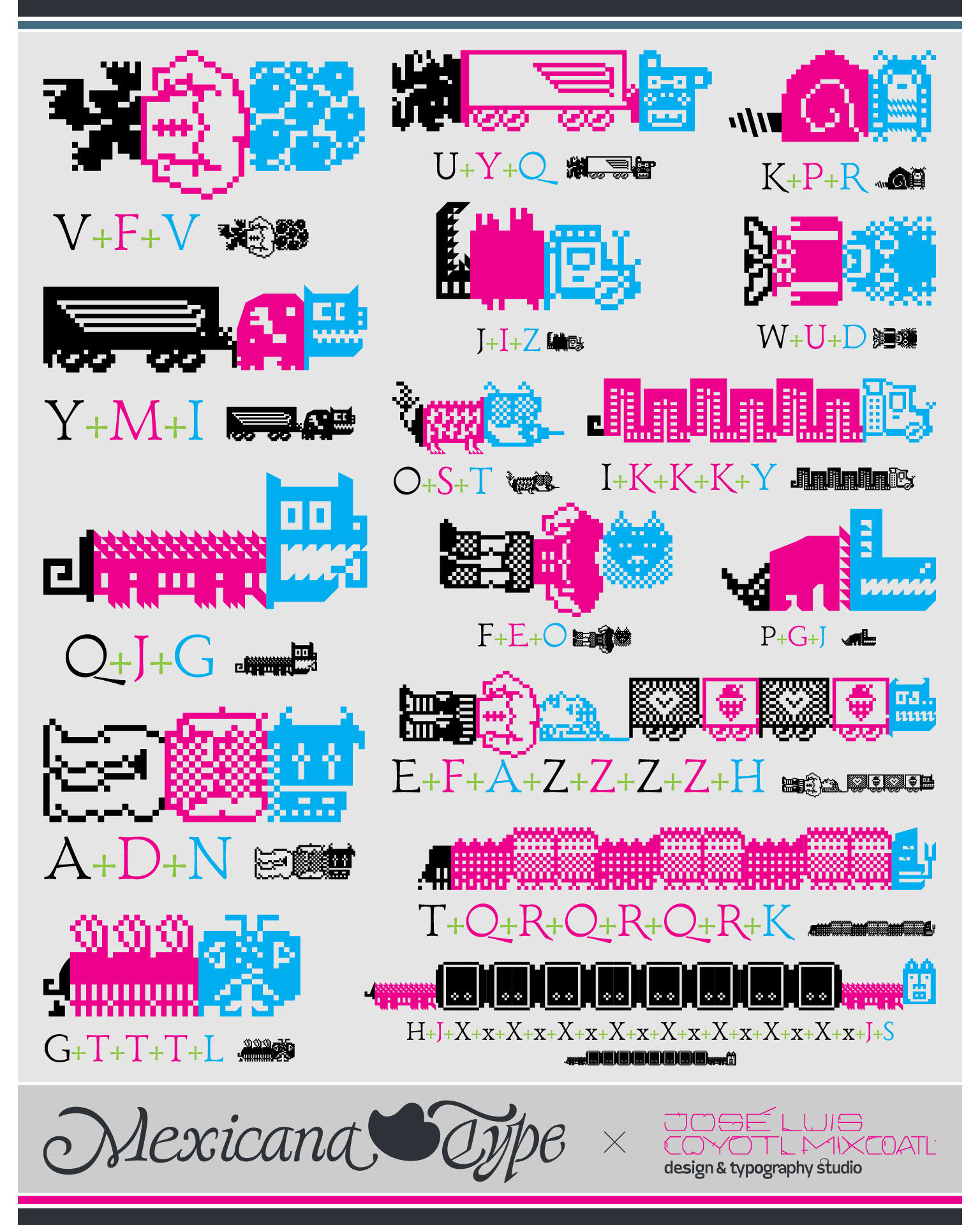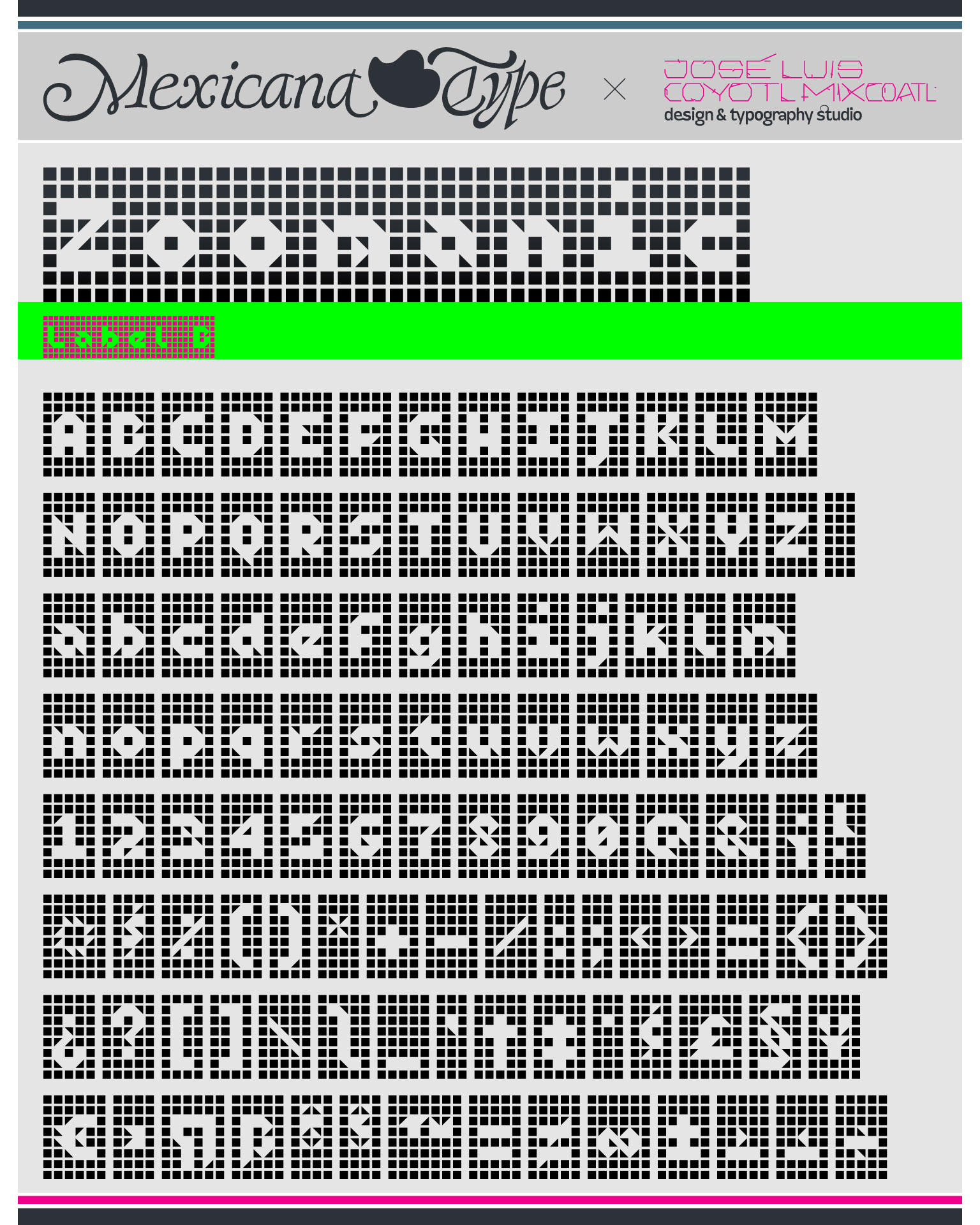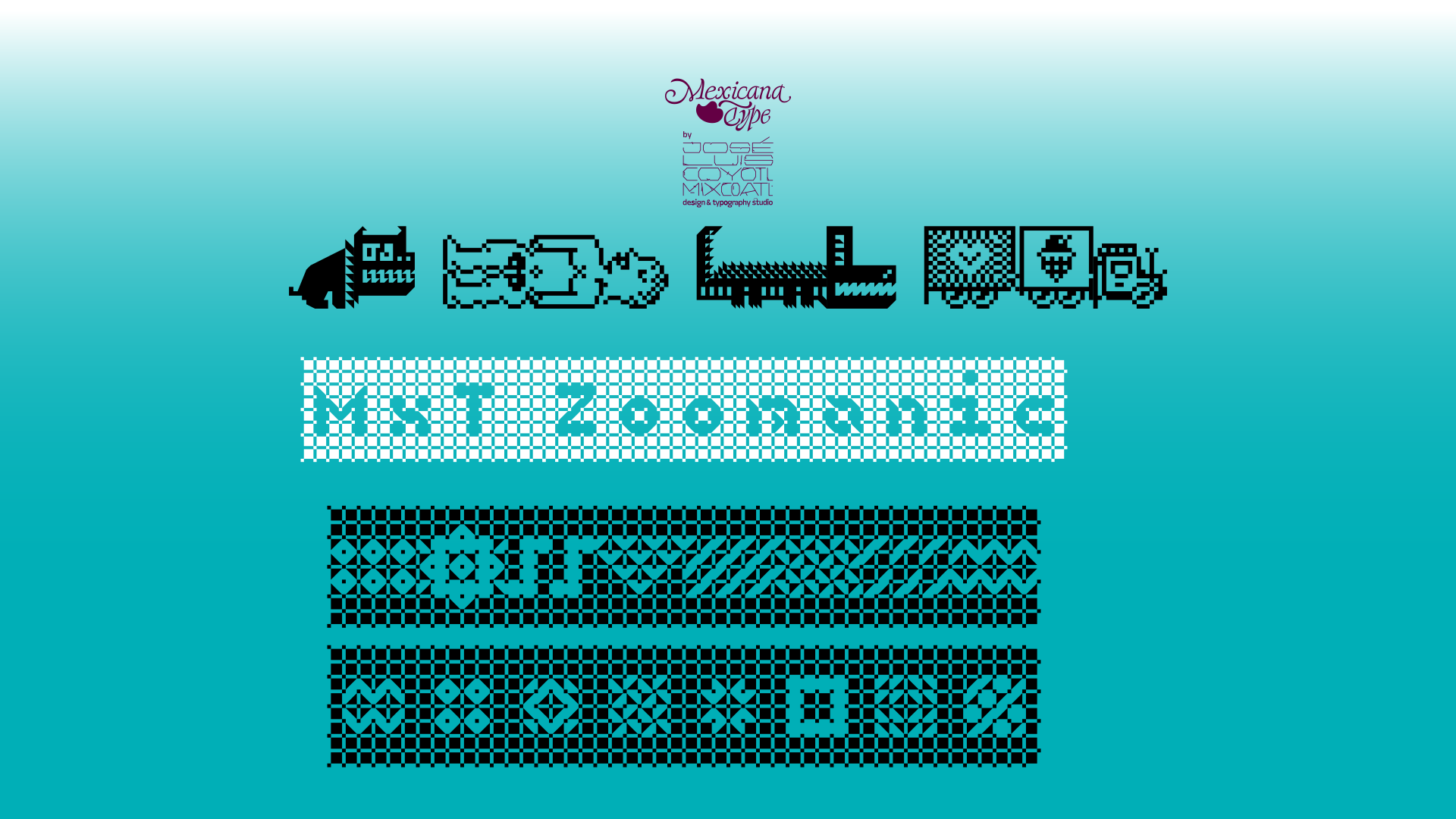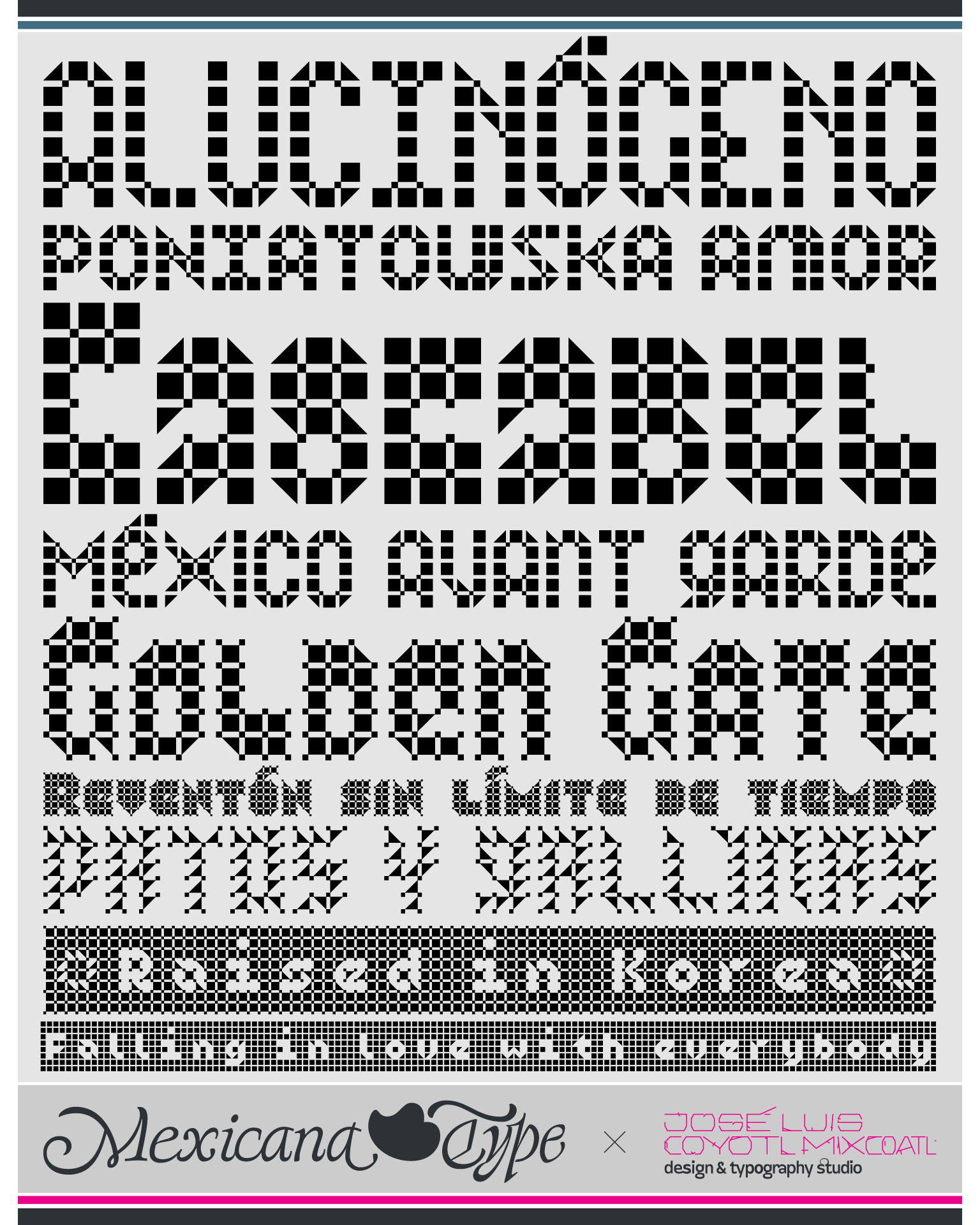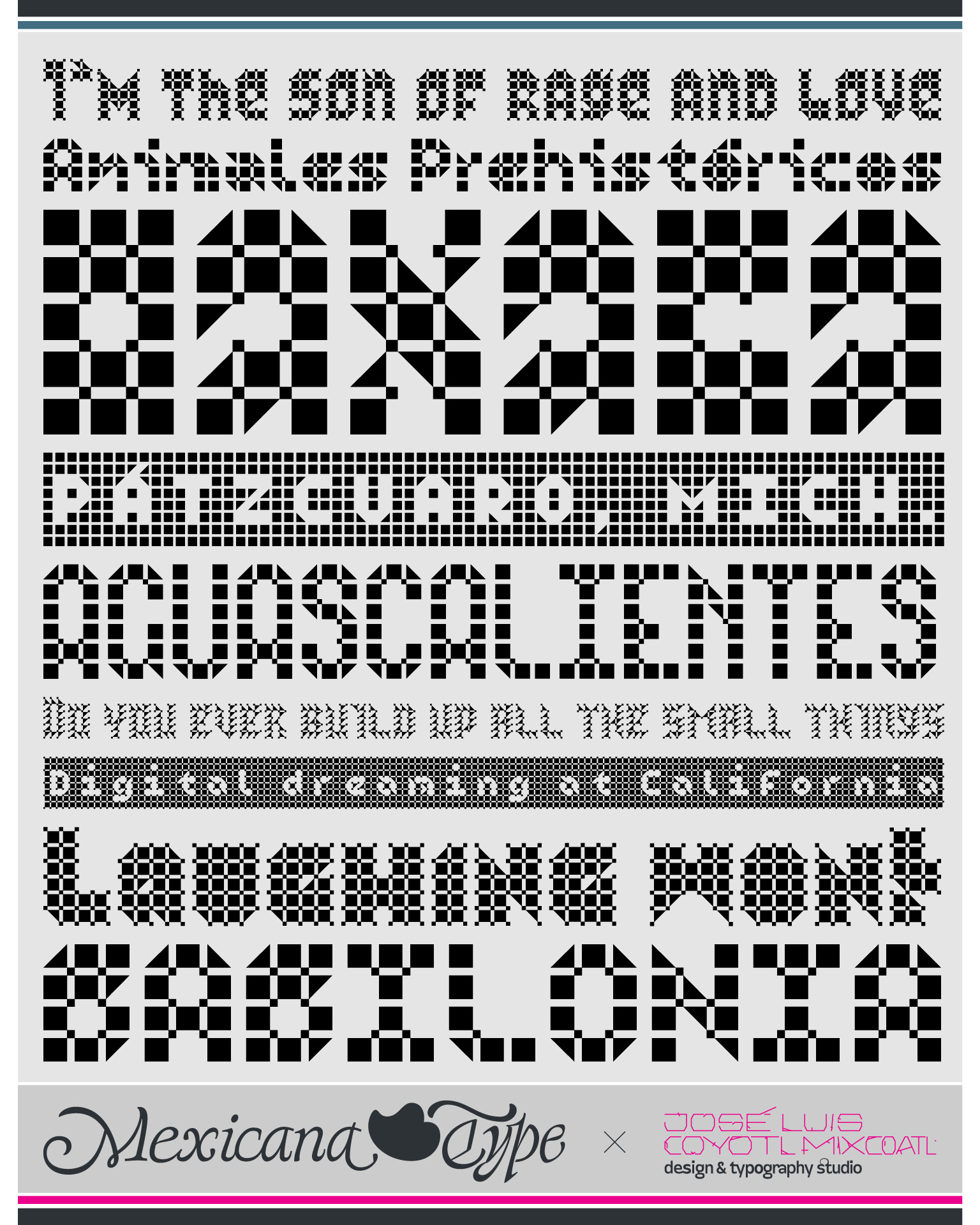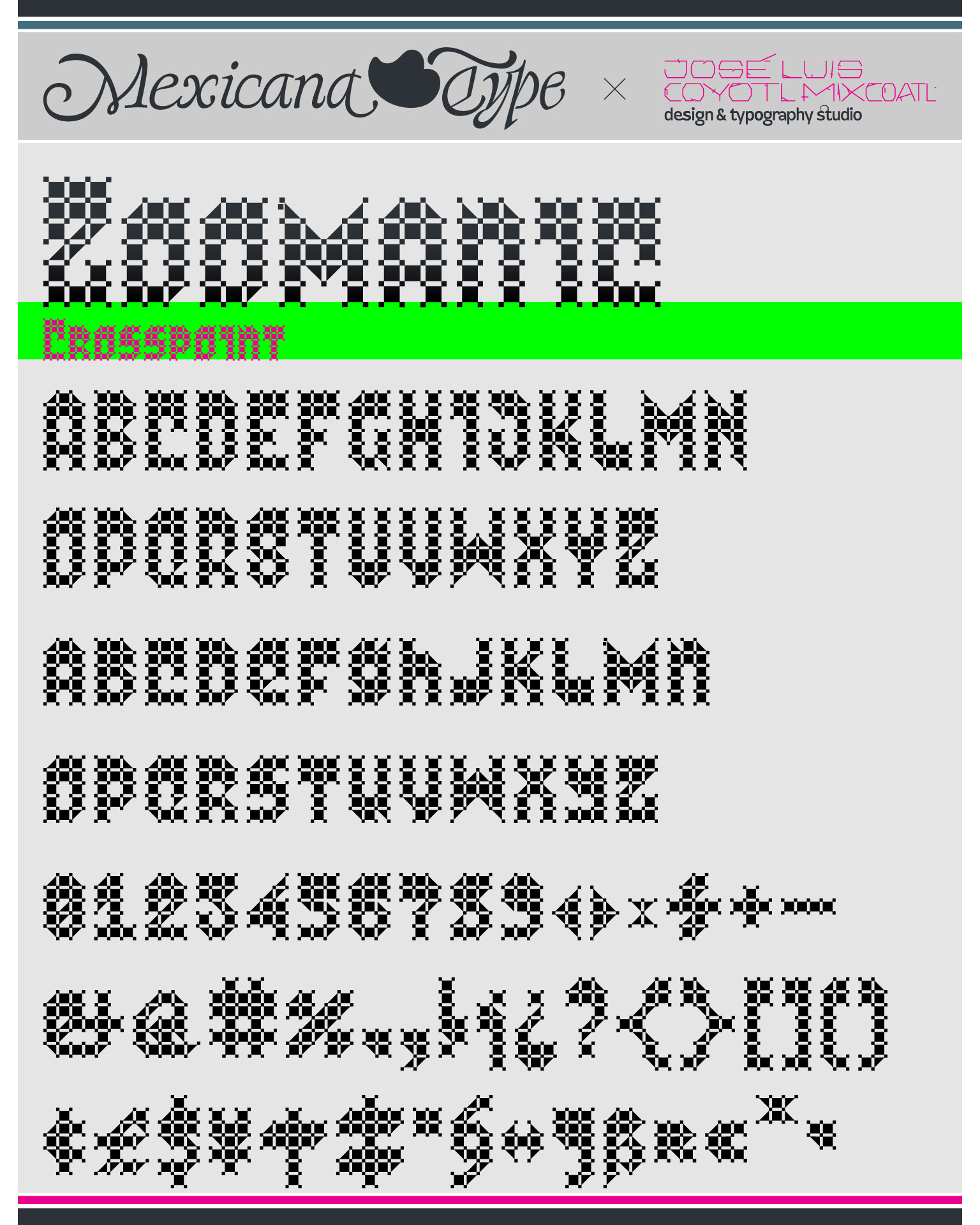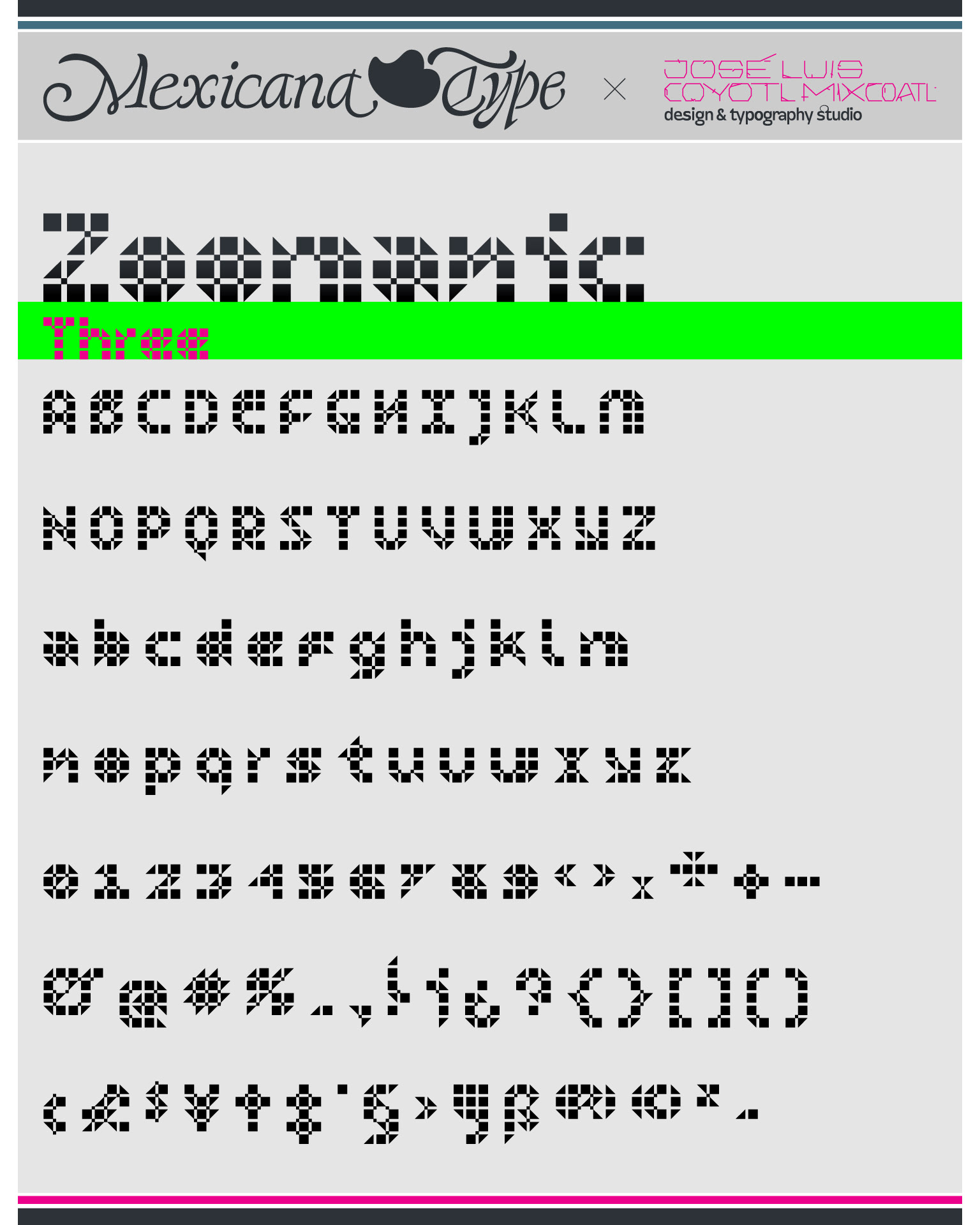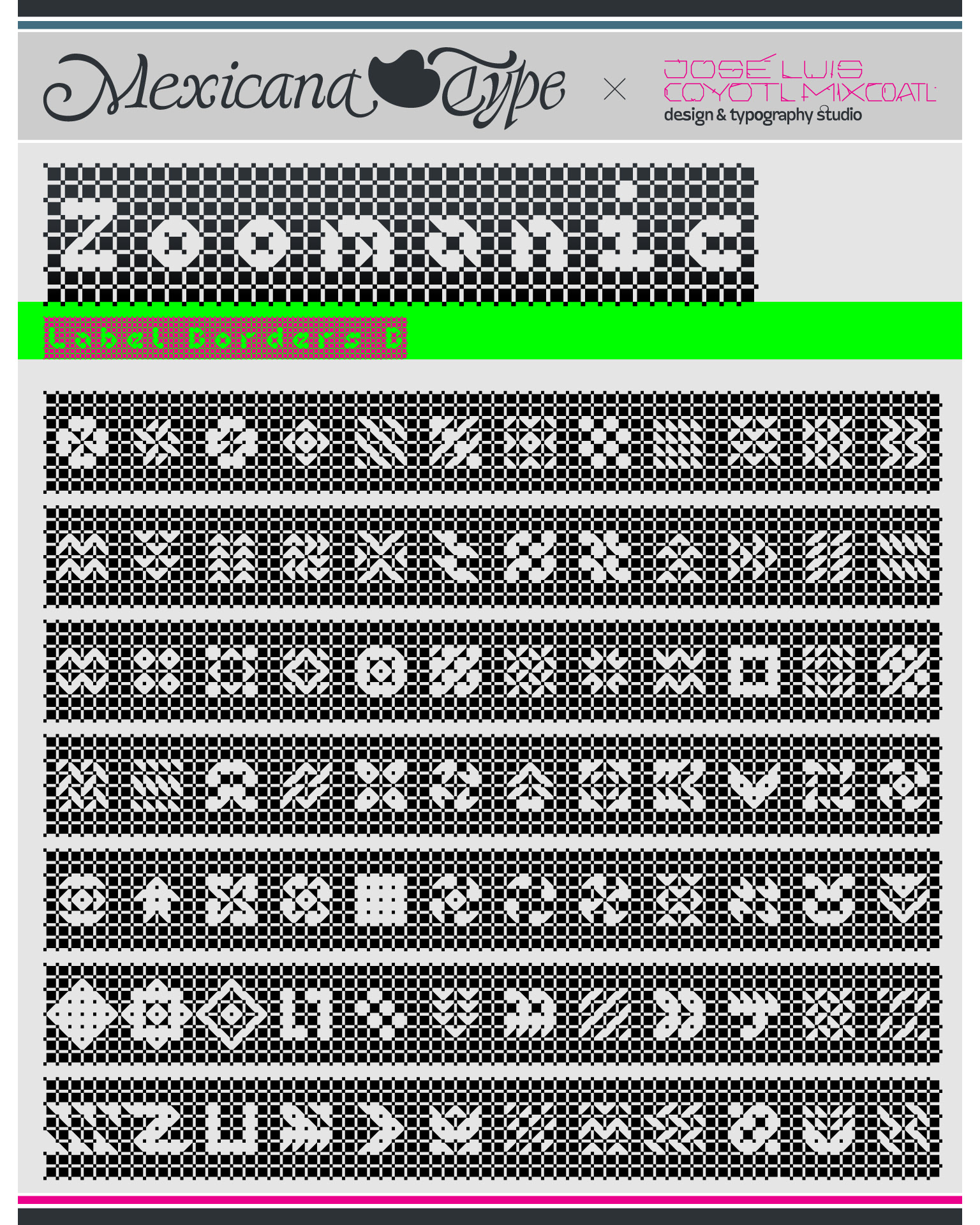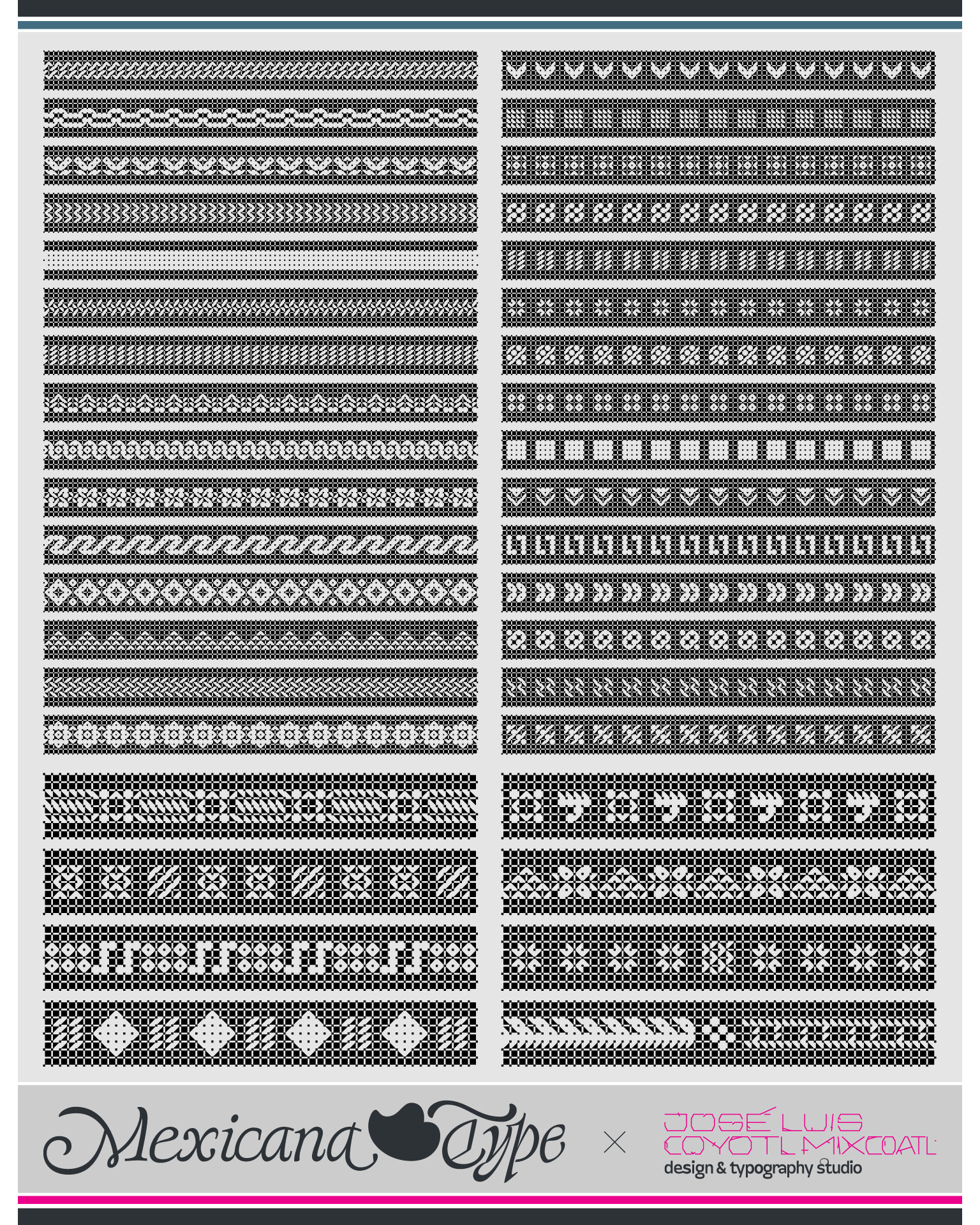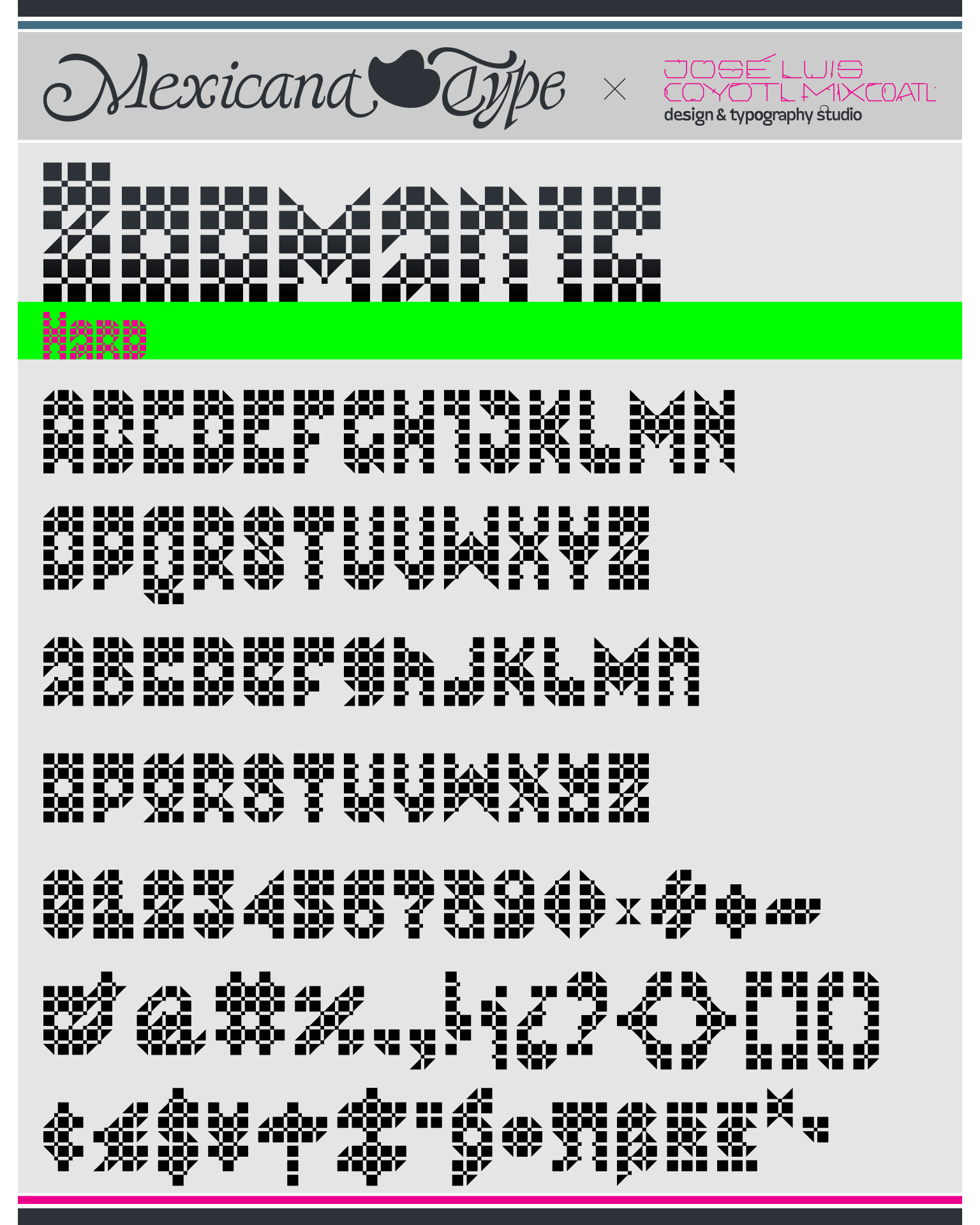
MxT Zoomanic es una super familia de fuentes tipográficas de las que inicialmente se diseñaron sólo una serie de dingbats para un proyecto especial, pero de manera natural se fueron diseñando algunos caracteres hasta que se tuvieron variantes suficientes para decidir completar sus mapas de caracteres, y progresivamente se fueron diseñando más pesos y variantes haciéndola muy amplia y versátil para combinarse entre si. Partiendo del reto de que se estaba diseñando con tres módulos básicos (Dos cuadrados y un triangulo), se lograron hacer combinaciones tanto hermanas como muy diferentes una de otras, y que por si mismas se volvieron en un juego de mexclas excentricas, lo que permitió experimentar no solo con variantes alfabéticas, sino también con los iniciales dingbats y también otras más para bordes y patronajes con un total de 15 variantes. Si bien no son del todo aptas para lecturas largas y fáciles, si tienen un juego gráfico muy interesante, además de que genera una textura y que le dan unas particularidades únicas.